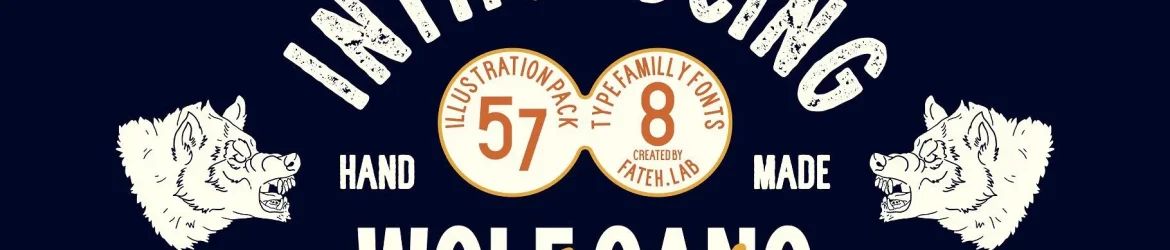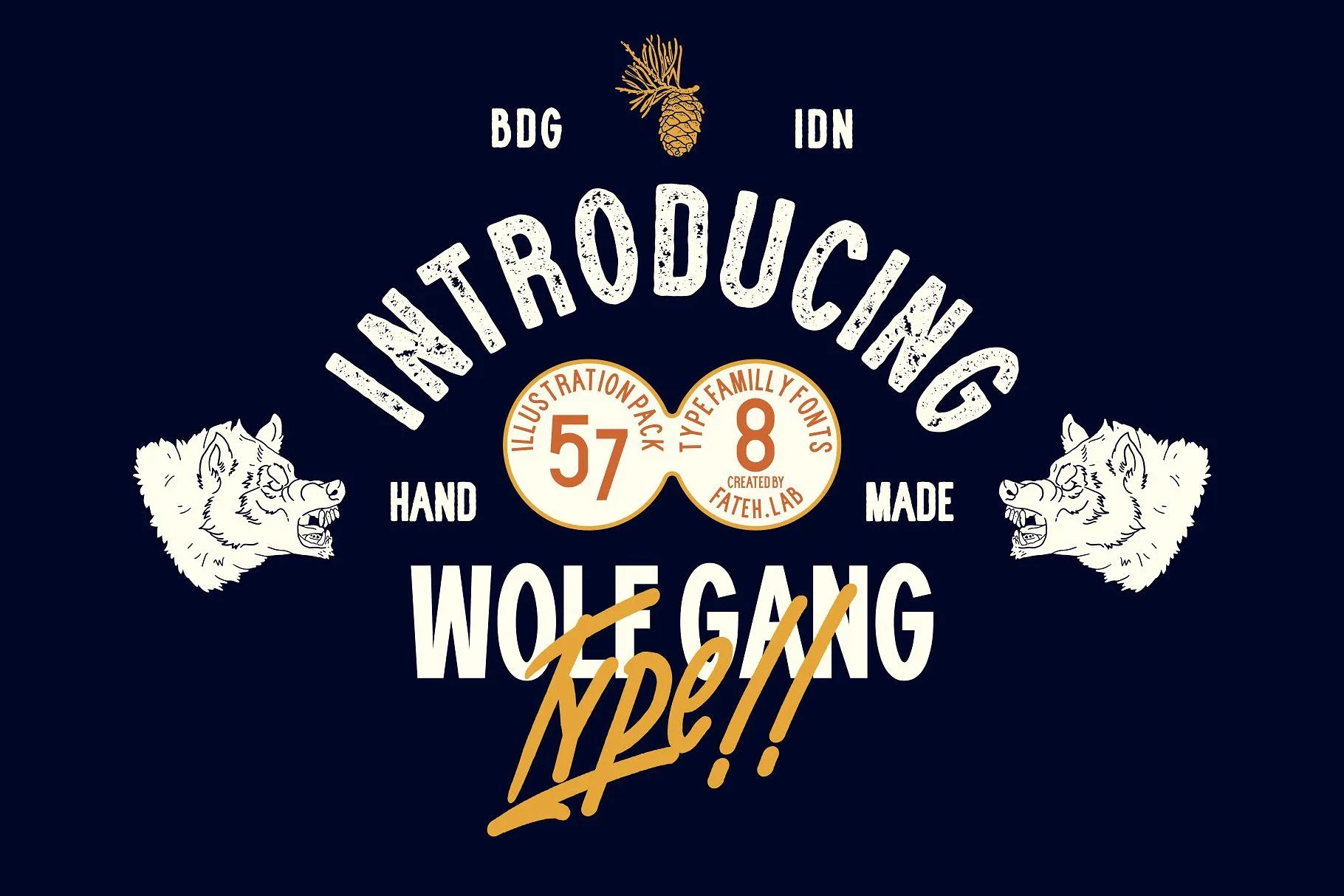
Wolf Gang Font Family – Fonte Grátis
Wolf Gang Font Family
WOLF GANG é uma fonte display criada com a intenção de evocar o desconcertante e selvagem mundo do norte. Este design inclui elementos pictóricos como lobos e outros seres animais que habitam a natureza, dando ao tipo um toque único e autêntico. Essa é uma fonte ideal para aqueles que buscam expressar um design inovador em t-shirts, logotipos, designs de cartazes, revistas, sinais e muito mais. Com seu caráter instigante e versátil, a Wolf Gang Font Family oferece aos criativos uma maneira única de estabelecer contato direto com o público através da sua mensagem visual. Opte por esta font para dar vida à suas criações, seja ela uma camiseta esportiva ou um cartaz publicitário.